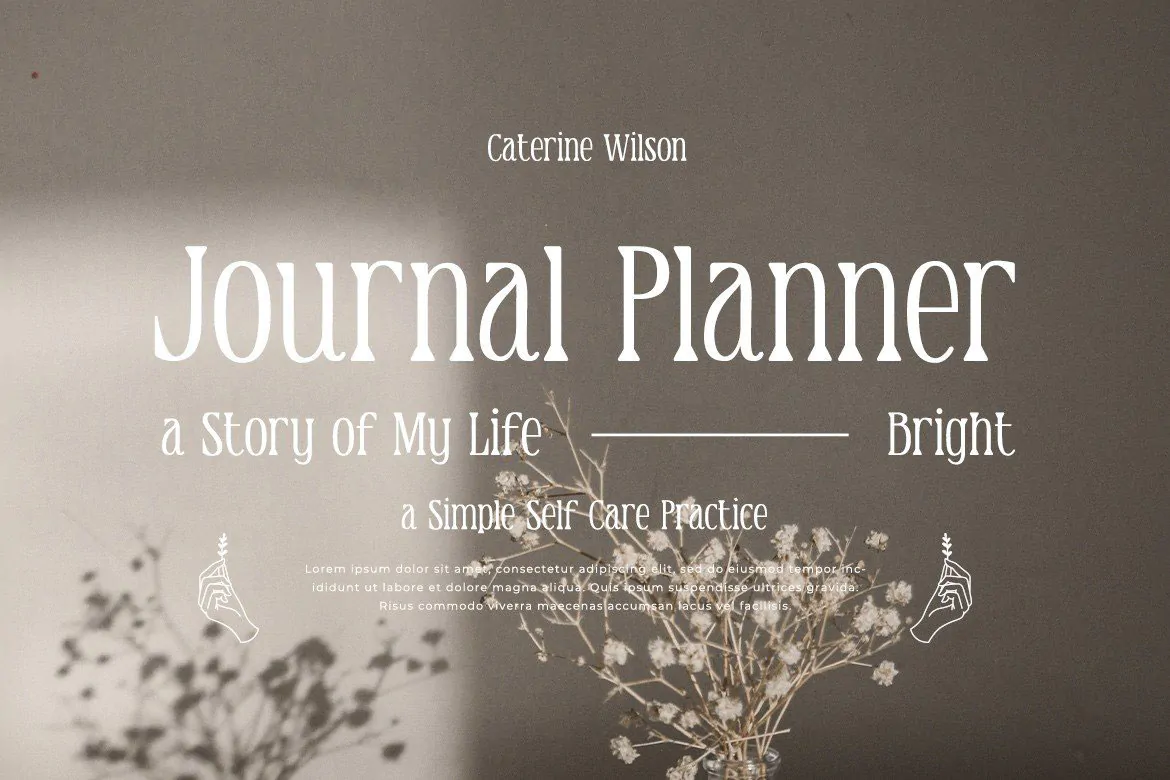
فونت شیک و لاکچری Tariel Valeri
فونت شیک و لاکچری انگلیسی
فونت شیک و لاکچری Tariel Valeri یک قلم زیبای انگلیسی است که مناسب برای استفاده در طرحهای گرافیکی مختلف به خصوص لوگوهای لاکچری و برندینگ میباشد. این فونت زیبا با وزن معمولی طراحی شده است که میتوانید از آن در طراحی انواع پوستر، کارت ویزیت، تراکت، بنر، بسته بندی محصولات، ظروف یکبار مصرف، آرایشی و بهداشتی و … میباشد.